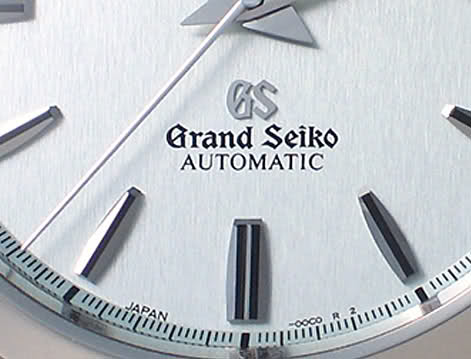
Armbanduhren »Grand Seiko«
Die höherwertigen Armbanduhren der Marke Seiko tragen die Bezeichnung Grand Seiko in einer Art gotischer Schrift. Weiß jemand, in welcher Schriftart dieser Name (s. Photo) ausgeführt ist und ob es ggf. diese Schrift als Font in digitaler Form gibt?
Danke Torsten. Die Clairvaux hat viel Ähnlichkeit mit der gesuchten Schrift, wobei die Seiko-Schrift etwas »holzschnittartiger« wirkt als die Clairvaux.